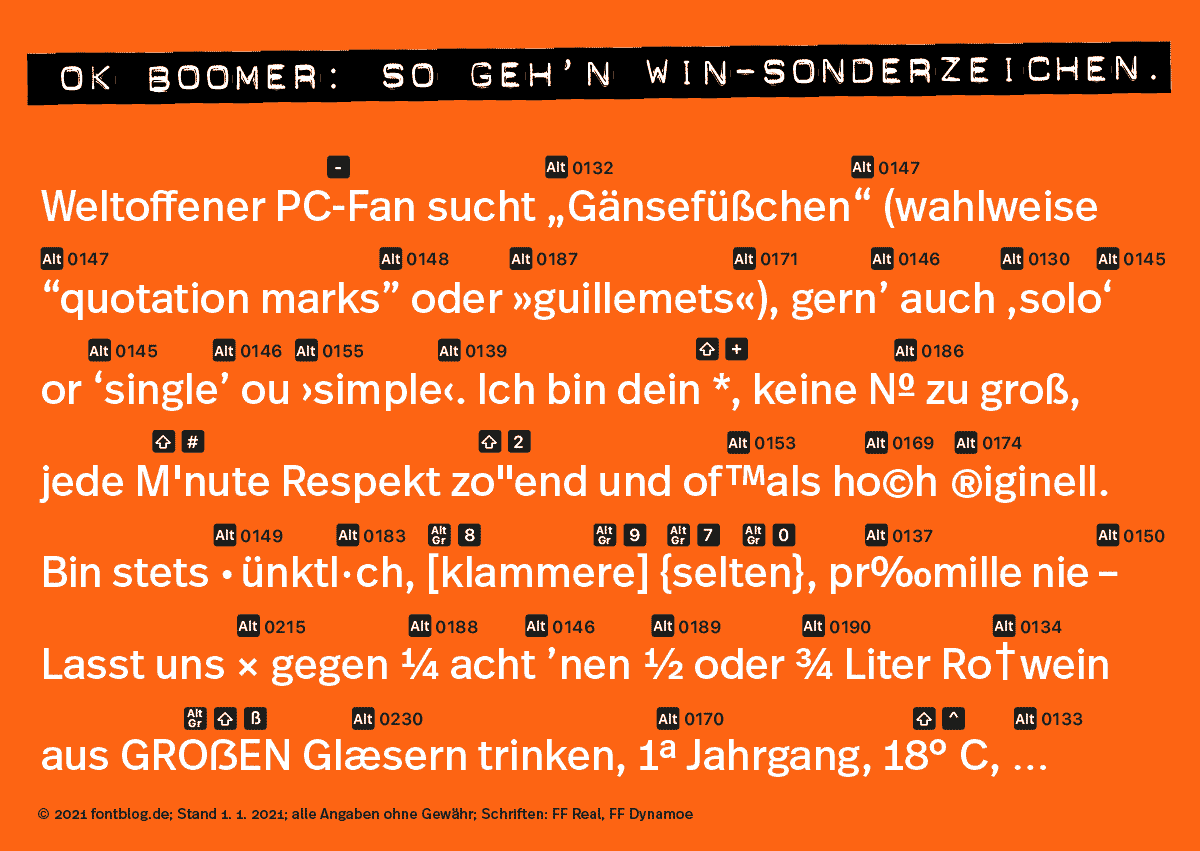
Gerade Anführungszeichen unten – wie?
suche die doppelten geraden Anführungszeichen unten. Kennt jemand den Code?
Aber das sind typografische Anführungszeichen, die darf ich hier nicht verwenden. Ich suche die geraden.
Ich welchem Kontext wird das verwendet?
Technikdokumentation. Die typo. Zeichen sind verboten.
Die »18° C« sind aber mal richtig falsch. Das Einheitenzeichen ist »°C« als Text oder auch »℃« als Zeichen (U+2103), aber nicht das Gradzeichen von Celsius getrennt. Muss also »18 °C« heißen.
Können dort nicht Zeichen verwendet werden, die im Font enthalten sind?
Mit dem Lektor sprechen ist sicher notwendig … 8-)
Die Zeichen für Minute und Zoll finde ich so auch nicht akzeptabel.
So, nun sollen wir nur obere Anführungszeichen verwenden. ;-):-D
… fachsprachlich stimmt das, »literarisch« kann man es auch andersrum machen, dann ist ° einfach ein Platzhalter für das quasi gesprochen gedachte »Grad«.
Sagt jedenfalls der Duden …
Naja, er wirbt mit »Nach dem aktuellen Stand der Rechtschreibregelungen«, das ist nicht nur Bestandsaufnahme, sondern Richtlinie. Dass jetzt »5° C« dem aktuellen Stand der Rechtschreibregelungen entspricht, war mir neu. Ich empfinde es auch weiterhin als Fehler, weil die Gradangabe allein nun mal einen Winkel bemisst.
Auf die Rechtschreibregelung kann man sich hier gar nicht berufen, da sie Sonderzeichen generell nicht regelt. Im Duden 1 (Rechtschreibung) steht die Empfehlung im Abschnitt »Die formale Gestaltung von Texten« (ehemals Vorschriften für den Schriftsatz). Mindestens seit 2000 (22. Auflage) steht dort:
Bei Temperaturangaben steht zwischen der Zahl und dem Gradzeichen ein kleiner Zwischenraum (Festabstand, geschütztes Leerzeichen), nach DIN 5008 ein ganzes Leerzeichen. Der Kennbuchstabe der Temperaturskala folgt ohne weiteren Zwischenraum.
Bei anderen Gradangaben wird das Gradzeichen ohne Zwischenraum an die Zahl angeschlossen. Beispiele: ein Winkel von 30°, 50° nördlicher Breite
Ich versteh nicht ganz – ist das irgendwie schlimmer als andere Veränderungen in Rechtschreibung, die sich über die Jahrhunderte und Jahrzehnte eingebürgert haben, die zwar „falsch“ waren, aber praktisch, oder eben einfach nur „ausreichend genau um nicht missverstanden zu werden“? So funktioniert doch Alltagssprache und -kommunikation seit jeher?
„5 Grad Celsius“ kann kaum missverständlich sein.
„5° Celsius“ ebenso nicht. Wie sollte das als Winkelangabe missinterpetiert werden?
Sogar „Es hat heute 5 Grad“ ist im Alltag kaum missverständlich.
Es wird also so gebraucht werden und sich einbürgern, weil's in der Praxis egal ist. Der Duden dokumentiert das eben so wie es gebraucht wird; und merkt ohnehin noch an: „5 °C (fachsprachlich nur so)“, um den eigentlichen Standard (sei das jetzt eine amtliche Rechtschreibung oder eine fachliche Konvention) hervorzuheben.
Missverständlich ist es natürlich nicht. Es fügt nur physische Schmerzen zu.
Aus dem Kontext erschließt sich natürlich auch, ob ein Winkel oder eine Temperatur gemeint ist. Mit dem Argument »weil's in der Praxis egal ist« ist können wir aber 95 % der Rechtschreipregeln über Board werven. Op das gewolld ist, stet auf einem anderen Platt.
Rechtschreiblich geregelt ist nur die ausgeschriebene Form für die Einheit: Grad Celsius. Alternativ kann sie nach Ziffern mit dem Einheitenzeichen °C geschrieben werden, das ist fachsprachlicher und typografischer Standard. Das Problem ist, dass der Duden nicht konsistent ist und in den Regeln für den Schriftsatz die tradierte Regel angibt, ihr im Wörterverzeichnis aber nicht folgt. Früher unterschied man fachsprachliche  (5 °C) und allgemeinsprachliche Schreibung (5° C), letztere ist aber immer seltener geworden. Selbst die DIN 5008:2020 gibt nur die Schreibung mit Leerzeichen nach der Ziffer an.
Möglich wären also: fünf Grad, fünf Grad Celsius, 5 °C.
Abweichend dagegen: fünf  °C, 5° Celsius
Der Unterschied liegt darin, ob sich etwas irgendwie weiterentwickelt (nicht: verbessert oder verschlechtert, nur verändert) ...
... weil die große Masse an Anwendern damit ebenso zurecht kommt und gar keinen funktionalen Unterschied zwischen zwei Schreibweisen sieht, also mal so und mal so macht ... dann ist diese Veränderung nicht zu stoppen, weder durch ein Regelwerk noch durch Nicht-Dokumentation der „falschen“ Schreibweise, sie wird einfach (auch) Konvention.
Grundsätzlich stimme ich da zu. Aber bei Grad Celsius ist das Gegenteil der Fall, hier hat sich nach und nach die fachsprachliche Variante etabliert und die andere verdrängt. Und fünf  °C kommt sicher gelegentlich im Schreibgebrauch vor, wird aber von den meisten Schreibenden als Fehler eingestuft (ebenso wie fünf % oder fünf €). Im Duden kommen selten, aber eben doch gelegentlich auch Fehler vor.